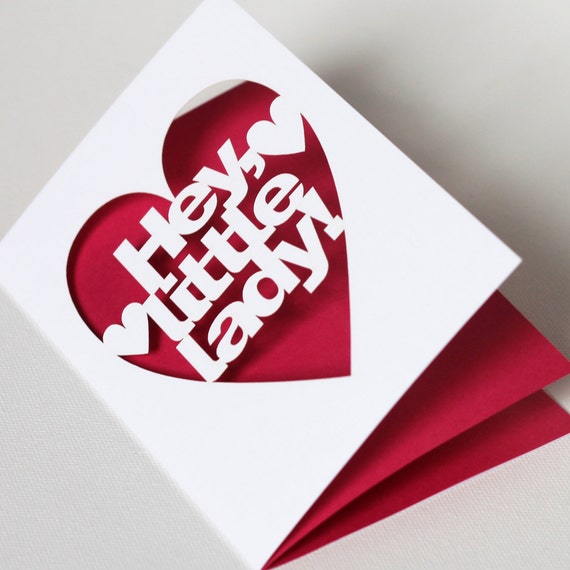
Có bác nào biết font này không? cho mình xin tên hay link nhé.:)
Mọi người cho hỏi đây là font
Mọi người cho mình hỏi mấy font này với, mình ít khi hỏi nhưng đã hỏi thì hỏi một thể. Heehee...:
Font này là font gì m.n nhỉ? Nhìn rất quen mà không nhớ tên luôn. Chữ "l" và "i" lại có chân cơ
#981: Cider Script, Buttermilk, Aphrodite Pro, Avo.
Mọi người giúp em với ạ , em kiếm font Family style: "futura medium" và " Futura Medium Italic " hoài không thấy
Mọi người giúp em tên font này với ạh, tìm hoài không ra, e xin cám ơn nhìu
#990: Sao bạn biết đây ko phải Kewl Script? :))
Các bác cho e hỏi đây là font gì thế ạ
Nhờ các bác tìm giùm mình font chữ trong ảnh này với, cảm ơn các bác nhiều ạ
#993: bạn có thấy nó giống Times New Roman không?
#994: Mình cũng thử thấy giống mà thanh ngang ở chân nó ngắn hơn font TNR. Chữ O nó thắt khít lại chứ ko như TNR mà
Tìm cả ngàn font na ná Times New Roman... Bạn có thể tìm với keyword "serif font", "display font" hoặc kết hợp "serif display", chứ giờ bảo mình đi tìm chính xác cái font serif na ná Times New Roman kiểu này mình nản lắm.